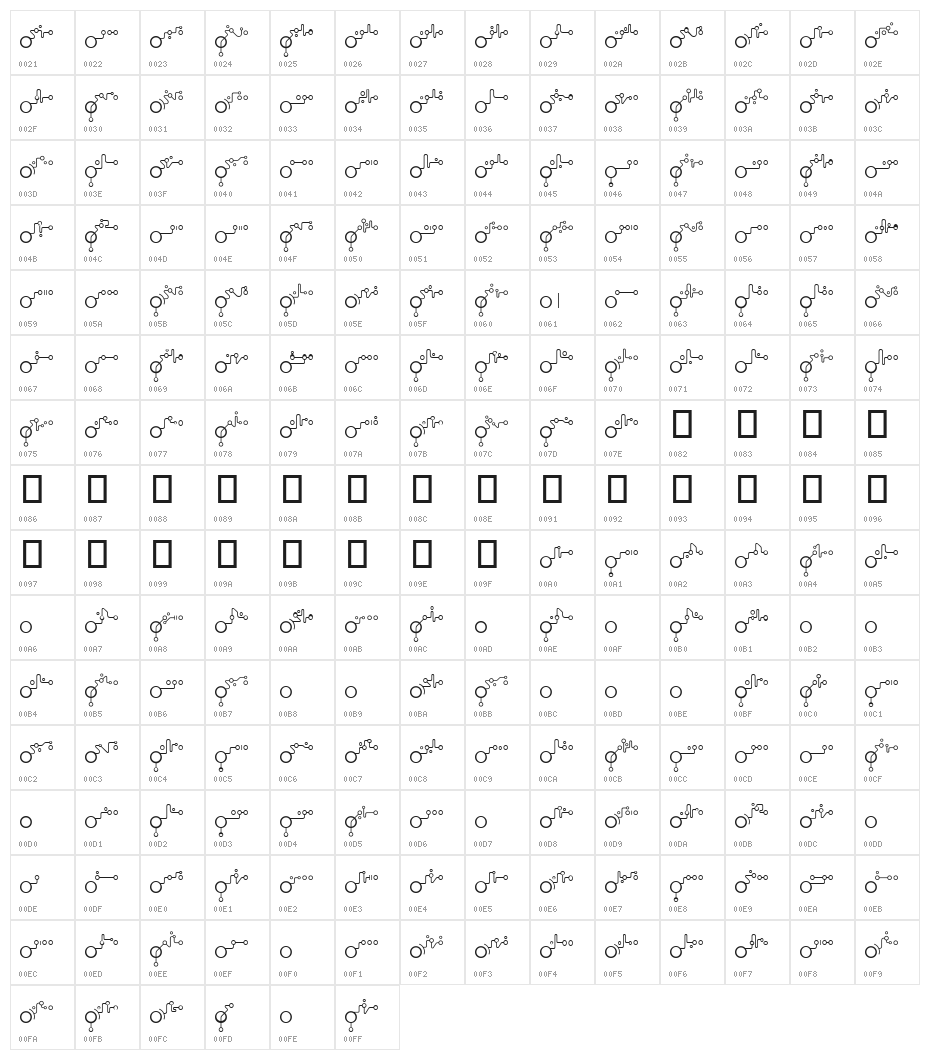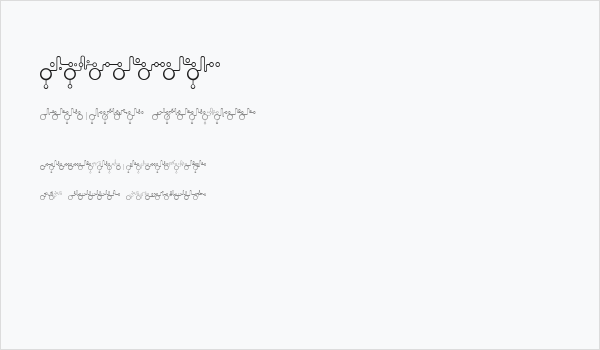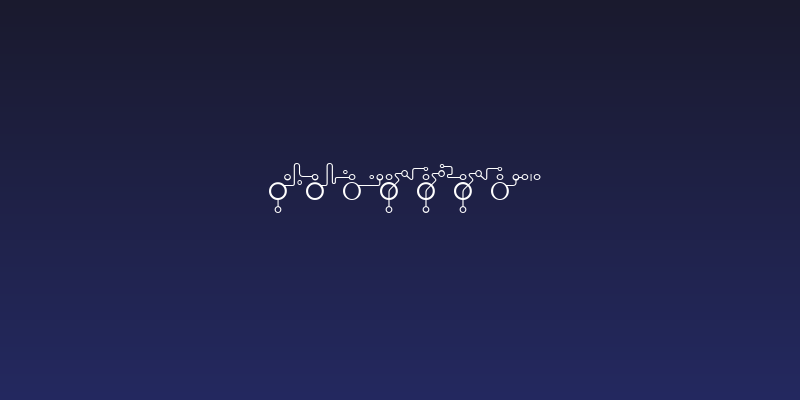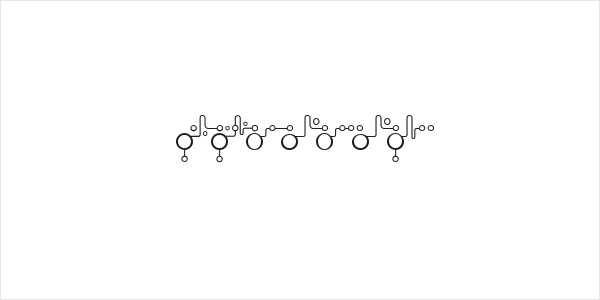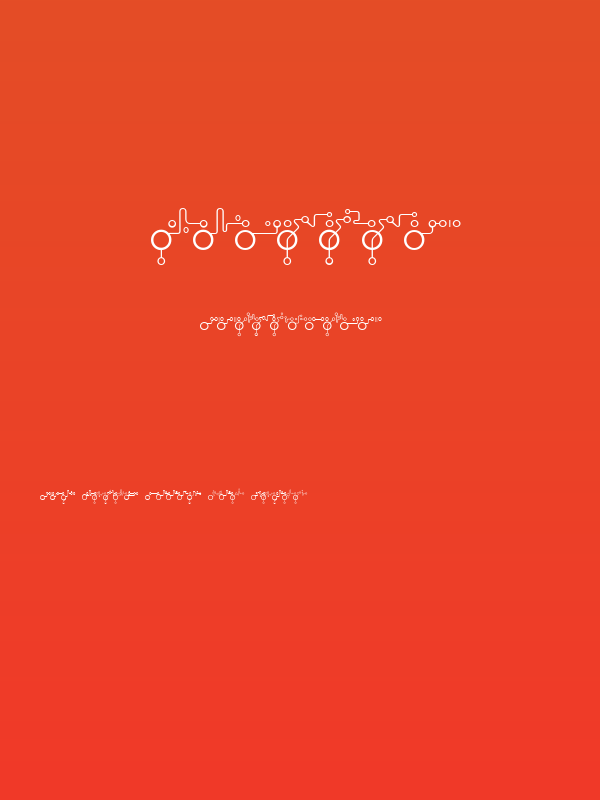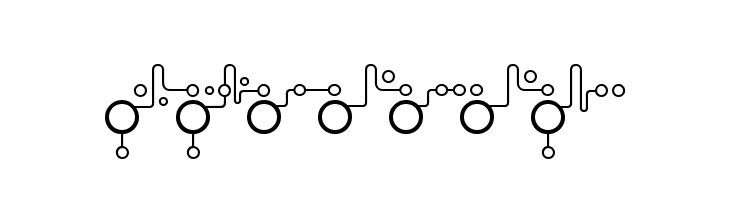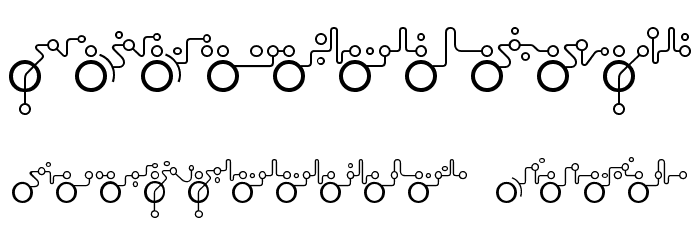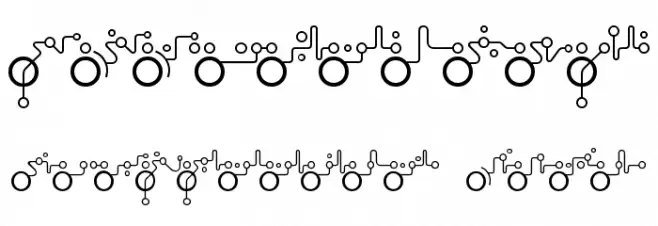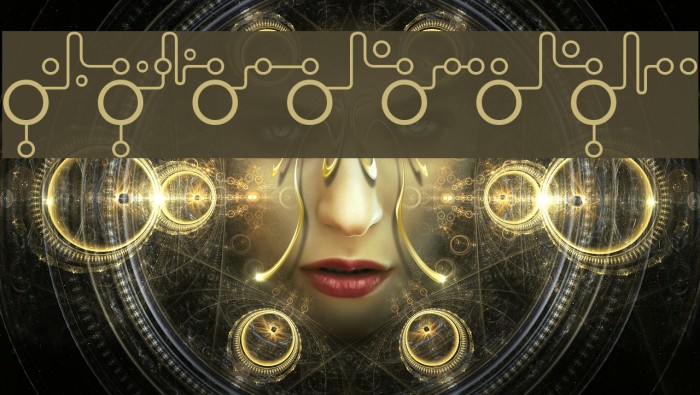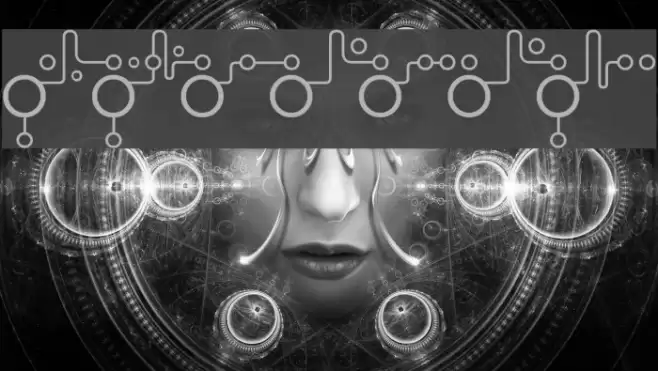
Echolot Font
| Stil general | Futuristic, Abstract |
| Caz de utilizare | Decorative elements, Art installations |
| Proiecte propuse | This design could be used for digital art projects, futuristic branding, or as a decorative element in tech-themed installations. |